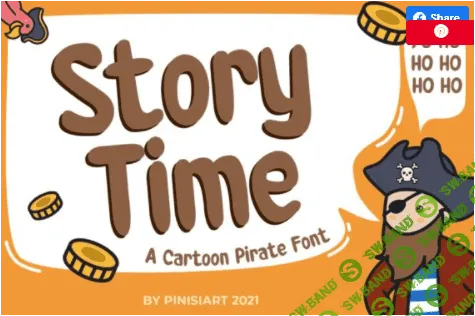
Название: Storytime Font (2022)
Storytime – детский шрифт без засечек
Если вам нужен шрифт, который заставит детей увлечься своей книгой, много читать и воспринимать всю информацию с веселым чувством, тогда Storytime — то, что вам нужно. Читаемость на высшем уровне, закругленный угол делает его более удобным.
Идеально подходит для детского книжного рынка, онлайн-игр, канцелярских принадлежностей, шрифта школьных принадлежностей, плакатов, названий фильмов, обложек YouTube, миниатюр YouTube, обложек страниц в социальных сетях и т. д.
Название: Storytime Font (2022)
Storytime – детский шрифт без засечек
Если вам нужен шрифт, который заставит детей увлечься своей книгой, много читать и воспринимать всю информацию с веселым чувством, тогда Storytime — то, что вам нужно. Читаемость на высшем уровне, закругленный угол делает его более удобным.
Идеально подходит для детского книжного рынка, онлайн-игр, канцелярских принадлежностей, шрифта школьных принадлежностей, плакатов, названий фильмов, обложек YouTube, миниатюр YouTube, обложек страниц в социальных сетях и т. д.